¿Dónde se han ido todas las flores? se preguntaba Pete Seeger en una de sus más famosas canciones. La misma pregunta nos hacemos nosotros sobre los venerables espacios utilizado en la composición tipográfica clásica con tipos de plomo y que parecen desaparecidos en la moderna composición digital. La «mecanización de la escritura» posibilitada por la aparición de la imprenta con tipos móviles, y que en Europa tuvo lugar a mediados del siglo XV, significó la estandarización tanto de los caracteres del alfabeto como de los espacios vacíos que separan las palabras o las letras.
La práctica tipográfica con tipos de plomo cubre un amplio espacio temporal en la historia de la imprenta, concretamente más de cuatro siglos, durante los cuales, y en particular a partir del siglo XVII en los que comienzan a aparecer los primeros manuales que dan cuenta de sus procesos y técnicas, se produjo un proceso de difusión y consolidación de las herramientas y materiales utilizados qué prácticamente llega hasta nuestros días y que se ha transmitido a través de tecnologías totalmente diferentes como han sido la fotocomposición y la autoedición digital.
¿Clásico o moderno?
Llegado hasta aquí, en un entorno totalmente digital, me preguntaría si es necesaria la implementación de la tipometría clásica (puntos Didot y pica) en los programas de maquetación como Indesign. ¿Hacen falta para, por ejemplo maquetar, un libro? ¿Nos proporciona más seguridad que el punto postscript? ¿Qué hacemos con el sistema métrico decimal?
Posiblemente pueda parecer un anacronismo seguir utilizando los puntos Didot. De hecho si seguimos conociéndolos, y utilizándolos, fue debido a que cuando aparece el sistema métrico decimal en Francia a finales del siglo XIX, el propio Napoleón intentó que los impresores y fundidores franceses adoptaran esta unidad de medida y solamente el alto coste de la adopción de la misma (había que tirar todos los tipos y el material de blanco existente y volver a fundirlos) evitó que se llevara a cabo.
Pero claro, el sistema métrico decimal se fue imponiendo en prácticamente todos los demás campos donde era necesario medir algo, así que ahora nos encontramos manejando un software estupendo de composición de página (Indesign) que contempla el uso de las unidades decimales, que como está realizado en USA también nos incluye las unidades del sistema anglosajón de medida (la pulgada), y solemos dudar a la hora de establecer en sus preferencias que unidad de medida tipográfica elegimos: Puntos didot, pica o postcript o los cíceros y las picas (que provienen también de los tiempos del plomo tienen ambos una dimensión de 12 puntos).
Pero vamos a ver esta cuestión algo más de cerca. Mi impresión es que está bien seguir implementando los puntos tipográficos clásicos y que, como veremos más adelante, tienen su utilidad práctica pero no para ser utilizados en todas las medidas de una publicación y sus componentes sino en aspectos concretos de la misma.
Respecto a si son más útiles los puntos “analógicos” o “digitales” yo lo que creo es que a menos que quieras comprobar tipómetro en mano los ajustes de una página, mejor establece como unidad los puntos Postscript.
Las medidas tipográficas
Para saber en que tipos de mediciones son útiles los espacios clásicos tipográficos, lo primero que tenemos que ver son los dos tipos de medidas que conviven en una composición tipográfica. Estas son las medidas absolutas y las relativas. Las medidas absolutas son las que sus dimensiones son fijas y se utilicen donde se utilicen siempre serán las mismas. Aquí entrarían los puntos tipográficos (un punto Didot equivale a 0,376 mm, un punto Pica equivale a 0,351 mm, un punto Postscript equivale a 0,352 mm) y los cíceros y picas (12 puntos en cualquiera de los dos sistemas). Si utilizamos el sistema métrico decimal hablaríamos de centímetros o milímetros. Un ejemplo de medida absoluta es una fuente tipográfica de 12 puntos.
Por su parte las medidas relativas no tienen un valor fijo y absoluto como las anteriores sino que se aumentan o disminuyen proporcionalmente conforme el objeto que miden aumenta o disminuye. Las medidas relativas las encontramos en los espacios blancos que acompañan a una tipografía en un tamaño concreto. Por ejemplo a continuación puedes ver el valor de los espacios correspondientes a nuestra tipografía de cuerpo 12. Estos son los espacios que en tipografía de plomo se utilizaban para separar letras y palabras, para indicar algún espacio mayor como el de inicio de párrafo y para completar las líneas:
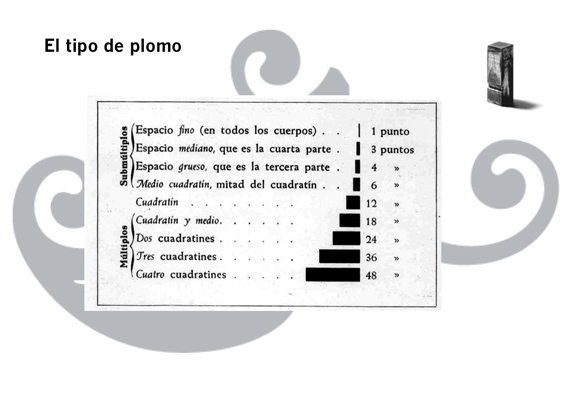
La unidad de todos ellos es el cuadratín. A partir del cuadratín los espacios se dividen o se multiplican. En nuestro caso vamos a hablar solamente de los espacios que dividen el cuadratín, que son los utilizados para medidas cortas como el espacio entre palabras o caracteres: Medio cuadratín, espacio grueso, mediano y fino.
Comentar en este punto que los que hayan visto este tema en textos o traducciones del inglés, habrán visto que el cuadratín lo denominan como espacio M, para el medio cuadratín espacio N, y para los demás espacios divisiones con referencia al espacio M.
Como hemos comentado que esta unidad es relativa significa que adoptará siempre el tamaño de la fuente en la que está incluida, así una fuente de 16 puntos tendrá un cuadratín de 16 puntos, un medio cuadratín de 8 y los espacios serán divisiones de 16. En este caso, y siguiendo el ejemplo con la fuente de plomo de 12 puntos los espacios que incluiría serían los siguientes.
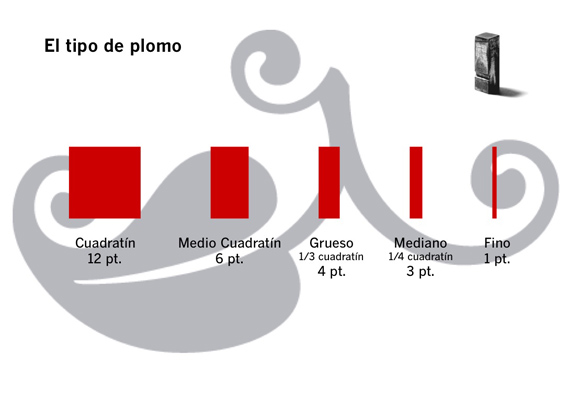
Asimismo, la anchura de los diferentes caracteres también está considerada en unidades de cuadratín (nosotros vamos a continuar citándolos con su término en español), y esto no cabe duda de que es una brillante idea. Por ejemplo Monotype basaba todos los anchos de los caracteres de sus diseños tipográficos dividiendo el cuadratín en 18 unidades. Todos los caracteres debían ajustarse a unidades completas siendo por tanto el más ancho de 18 unidades y el más pequeño de 5 unidades.
También en tipografía digital se siguen utilizando las unidades de cuadratín pero en este caso las posibilidades en cuanto a dibujo de los caracteres y ajuste de la composición son bastante más amplias. Valga como ejemplo que las fuentes PostScript utilizan un cuadratín dividido en mil unidades. Una de las facilidades es, por ejemplo, no tener que realizar una tabla de pares de kerning para cada tamaño que utilicemos ya que otra vez con saber el tamaño que vamos a utilizar el programa realiza los ajustes necesarios en los programas, lo mismo que si cambiamos el tamaño de la fuente que estamos utilizando.
Puntos o centímetros
Por lo tanto en Indesign conviven los dos tipos de medidas y nos queda por saber donde aplicarlas y donde funcionan mejor. Bajo mi punto de vista lo más sensato es trabajar con unidades del sistema métrico decimal en el apartado de definición del tamaño de página, márgenes e incluso de anchura de columnas dejando las unidades clásicas para definir los elementos microtipográficos como el tamaño de la tipografía, espacio entre líneas y línea base.
Seguramente nos es más fácil imaginar el tamaño de una publicación en centímetros que en cíceros así como el tamaño de sus márgenes y el ancho de columna (aunque en este caso algunos prefieren utilizar los cíceros).
Al contrario imaginamos mejor la dimensión de un tipo en puntos tipográficos que en milímetros así como el espacio entre las líneas y el tamaño de la línea base (de esta forma nos aseguramos realizar una rejilla tipográfica coherente).
Y esto es así, creo que no vale la pena quedarnos solamente con un sistema de unidades porque lo que se ajusta bien a un apartado, no lo hace tanto en otro.
Además, Indesign funciona como una calculadora excelente que ajustando en sus preferencias la medida de “salida” que deseamos utilizar podemos introducir la que queramos cuando estemos definiendo algún parámetro que el programa la transforma en la que hemos indicado.
Composición y justificación
En la composición manual con tipos de plomo, el compositor iba componiendo la línea, de acuerdo a la medida elegida, componiendo las palabra y utilizando los espacios para separarlas (un espacio grueso era el aconsejado para este fin). Una vez llegaba al final de la línea se procedía a su justificación, esto es darla la medida exacta, para lo cual iba cambiando los espacios por otros más anchos o más estrechos según eran los requerimientos de alargarla o acortarla.
En la composición digital se ha perdido ese “contacto íntimo” con la composición de las líneas de un párrafo. Yo suelo decir que en este caso debemos buscar en la composición el aspecto de un “bosque tupido”, sin claros en el mismo que llamen excesivamente la atención. Para lograr esta textura en la composición, el maquetador suele especificar unas opciones de párrafo conocidas como “P&J´s” (partición y justificación) que le sirven para indicar al “motor de composición” de la aplicación los diferentes parámetros (optimización del espacio entre letras y palabras básicamente) que debe utilizar en la composición del texto.
Y los espacios clásicos, ¿dónde se han ido?
La buena noticia es que todavía están contemplados en Indesign. La mala es que la traducción del programa al castellano no deja claro a que se refiere la opción donde los contempla.
Efectivamente, los espacios en blanco que podemos añadir manualmente están agrupados en una opción llamada Insertar espacio en blanco pero la “madre de todos los espacios”, el cuadratín, está traducido por espacio largo con lo que su significado genera dudas sobre la cantidad de espacio que añade. Por extensión pasa lo mismo con el medio cuadratín que se llama espacio corto y los subsiguientes espacios que no dejan bien claro su valor (extrafino, fino tercio y cuarto), si no conocemos de donde viene.
En conclusión
Como he apuntado más arriba la composición digital de texto no reside en ir colocando a mano los espacios heredados de la composición con tipos de plomo, pero creo que su implementación en las versiones en castellano de programas como Indesign ha dejado mucho que desear.
Una traducción que hubiera incluido los términos cuadratín y medio cuadratín, o que incluso hubiera dejado la denominación anglosajona de espacio m y n, hubiera ayudado sobremanera a comprender la naturaleza y dimensión de esos espacios que, como las meigas… “existir, existen”.